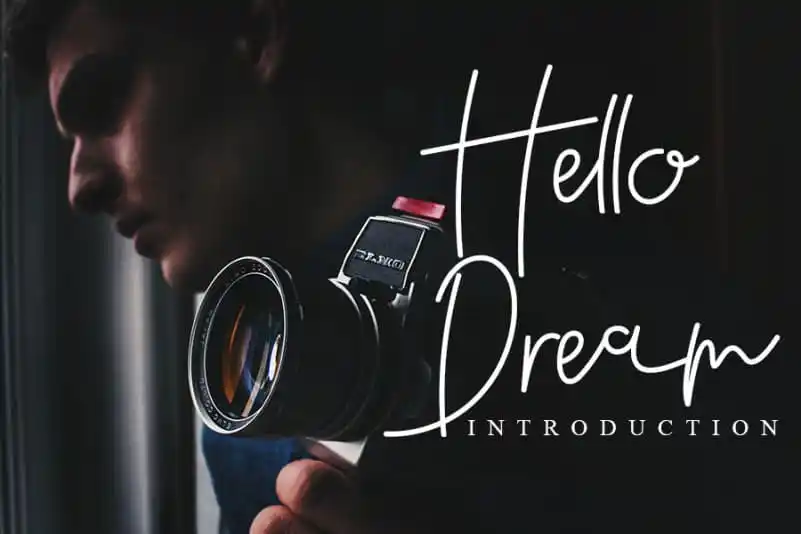
Hello Dream Handwritten Font – Download Grátis
A Hello Dream Handwritten Font é uma escolha perfeita para quem procura personalidade em cada letra. Com seus traços elegantes e influências clássicas, esta fonte mantém um toque de sofisticação enquanto se apresenta com frescor moderno. Suas opções versáteis permitem que esteja presente tanto nos recados quanto nas peças de design mais elaboradas, tornando-a uma escolha sólida para quem busca criar designs distintivos e criativos. Ideal tanto para a criação de etiquetas e títulos, como para projetos em papelaria, esta fonte transmite não apenas estilo, mas também um toque pessoal que certamente irá se destacar. É perfeita para designers amadores e profissionais em busca de uma maneira única de expressar suas ideias no mundo do design gráfico.